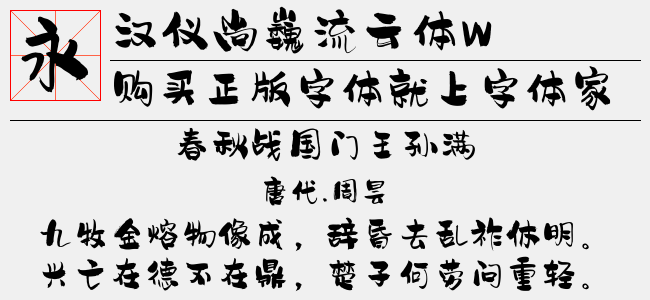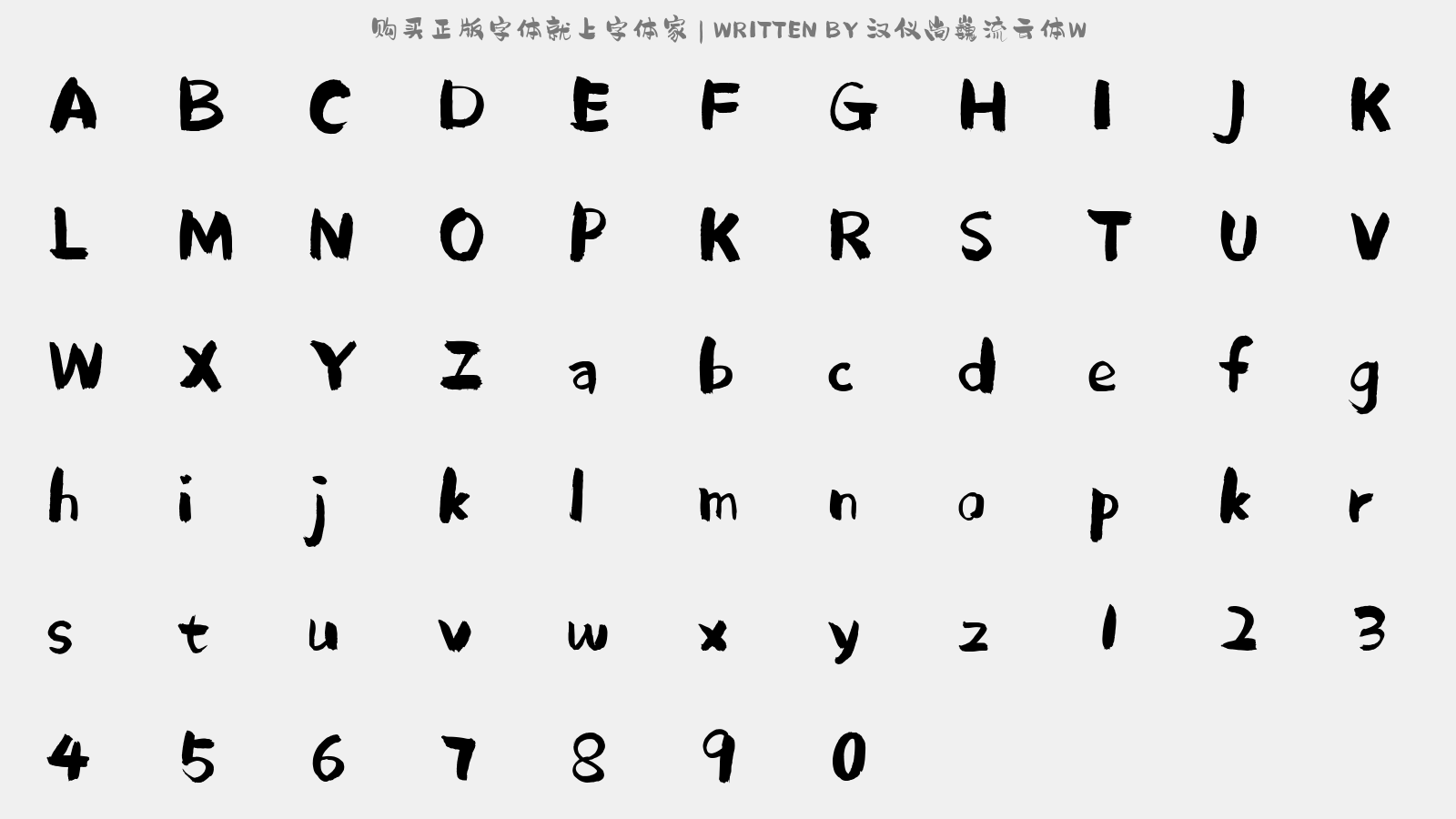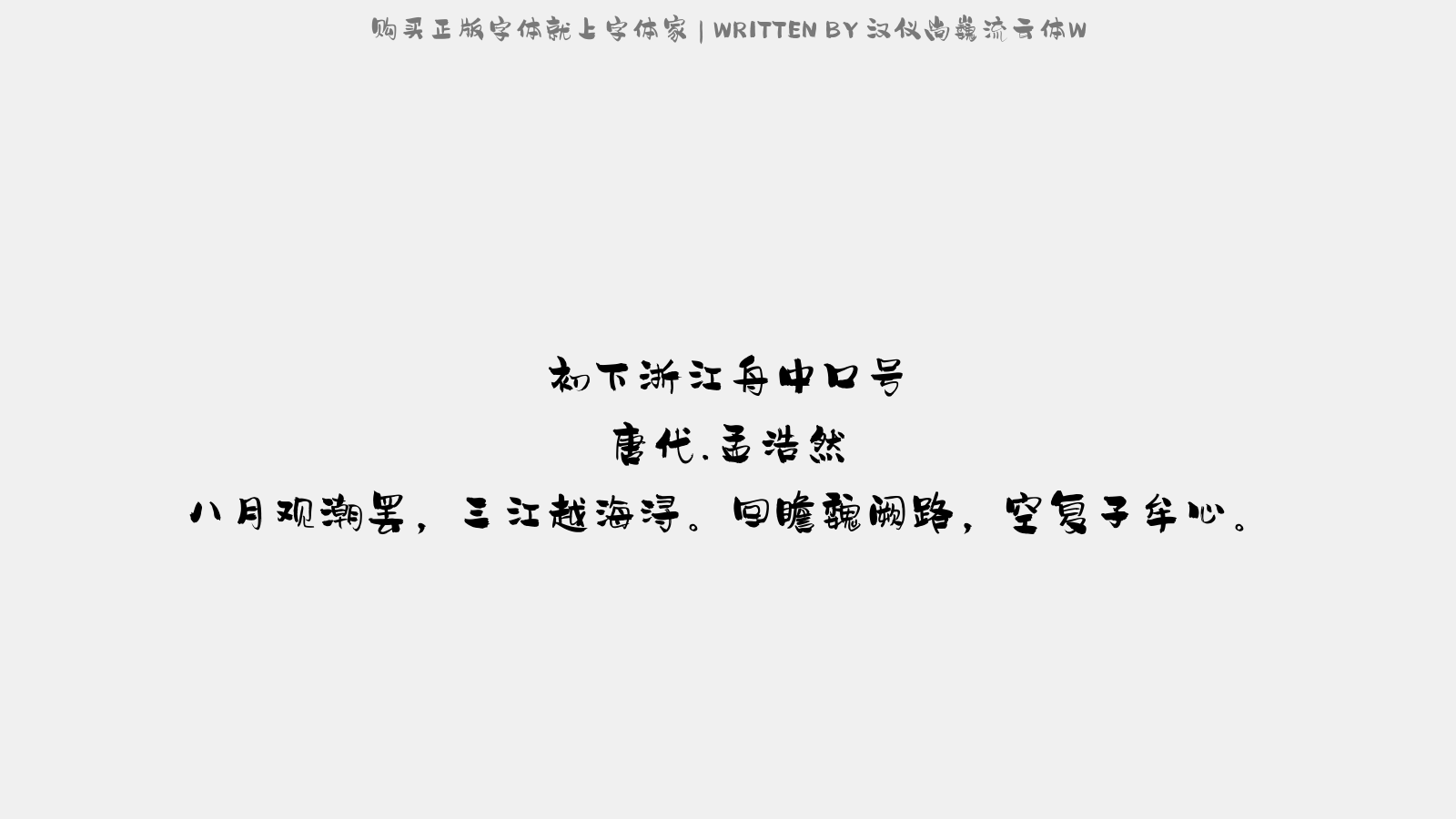
汉仪尚巍流云体W
字体作者:汉仪字库
字体名称:汉仪尚巍流云体W
字体字数:6763个汉字及26个英文大小写字母
字体家族:汉仪字库
书体类型:书法字库类
字体公司:北京汉仪科印信息技术有限公司
汉仪尚巍流云体W
汉仪尚巍流云体W是汉仪字库开发的一款适用于非常广泛的中文字体。该字体线条非常粗壮,笔画遒劲灵动,连笔张弛有度,如诗般优雅洒脱,且整体效果非常不错,能够应用于文本装潢、信息展示、网页设计、篆刻制模、数据制作、装潢设计、计算艺术设计、视觉设计、字帖等一切合法应用场景。
汉仪尚巍流云体W - 初下浙江舟中口号
汉仪尚巍流云体W - 章台月
汉仪尚巍流云体W - 赠王建司马
汉仪尚巍流云体W - 大写字母/小写字母/数字